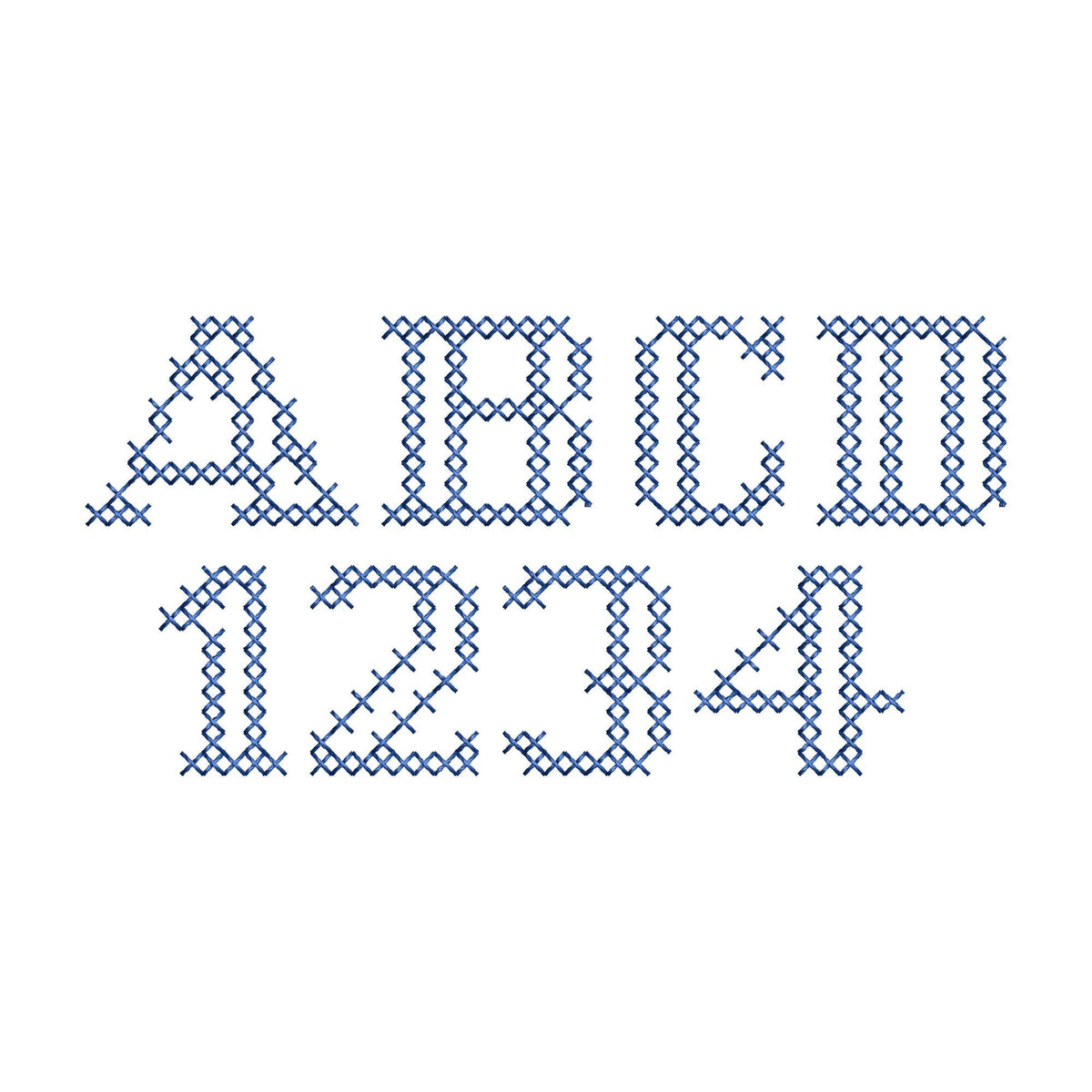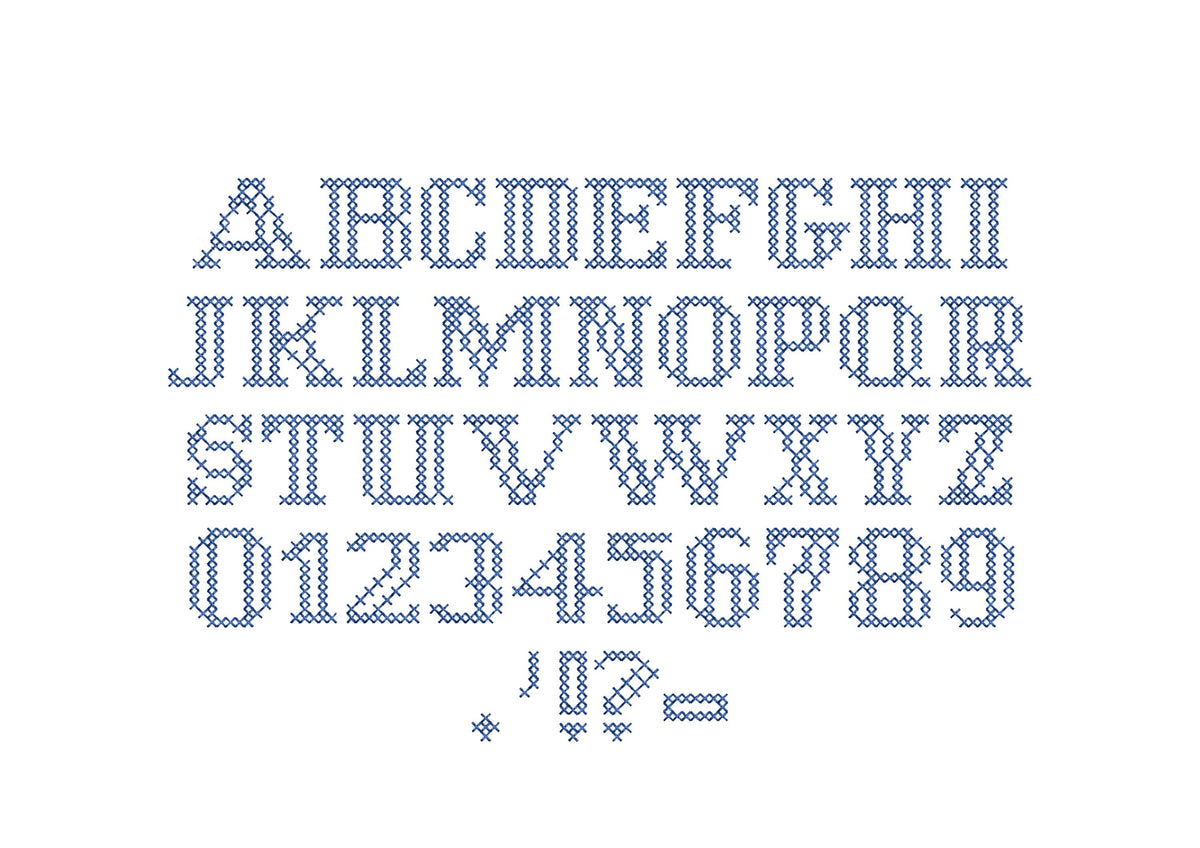
Font Authentic a punto croce
Un autentico font stampatello marcato a punto croce in stile folk, in misure minuscole. Delizioso per nomi, frasi e sampler.
Le lettere sono in quattro mini misure: 18, 23, 25 e 30 mm. Punti puliti a forma di X che sembrano un tradizionale punto croce contato. Include lettere maiuscole dalla A alla Z, numeri da 0 a 9 e punteggiatura.
- Font stampatello a punto croce autentico
- Maiuscole dalla A alla Z, numeri da 0 a 9, punteggiatura